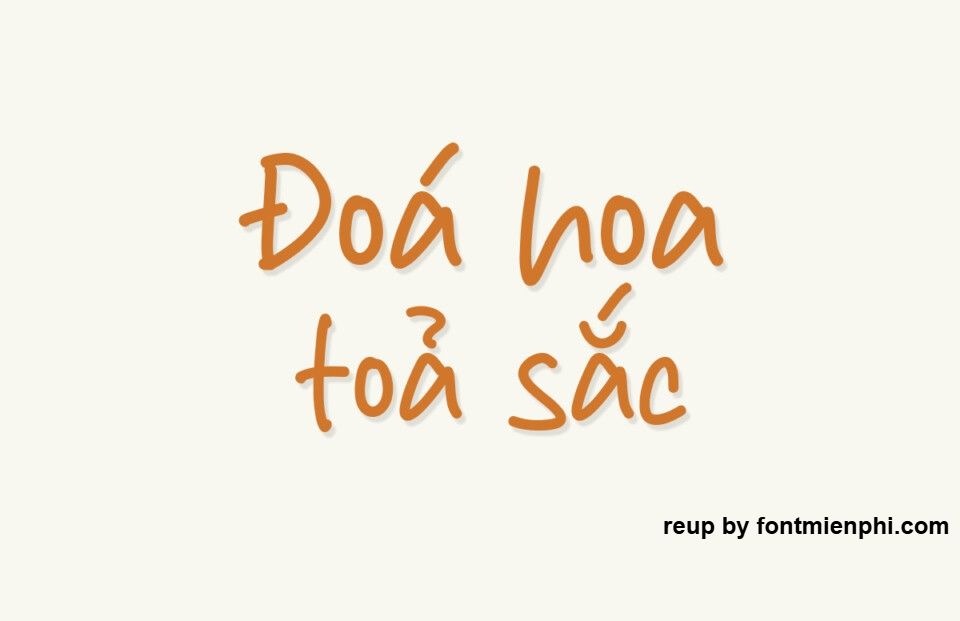
Font Việt hóa 1FTV VIP Privilege People
Font Việt hóa 1FTV VIP Privilege People là giải pháp typography hoàn hảo dành cho các nhà thiết kế đang tìm kiếm sự kết hợp giữa nét hiện đại, tinh tế và sự chuẩn mực trong ngôn ngữ tiếng Việt. Với bộ ký tự được chăm chút kỹ lưỡng cùng các đường nét sang trọng, bộ phông chữ này giúp mọi tác phẩm đồ họa trở nên nổi bật và ghi dấu ấn mạnh mẽ trong lòng người xem. Đây chắc chắn là công cụ không thể thiếu trong thư viện tài nguyên của những ai theo đuổi phong cách thiết kế chuyên nghiệp và đẳng cấp.
Font Việt Hóa 1FTV VIP Privilege People – Phông Chữ Sang Trọng Đột Phá Cho Thiết Kế Đẳng Cấp
Trong thế giới thiết kế đồ họa hiện đại, typography đóng vai trò như cầu nối cảm xúc giữa thương hiệu và khách hàng. Một phông chữ đẹp không chỉ giúp truyền tải thông điệp văn bản một cách rõ ràng mà còn định hình phong cách, gia tăng giá trị thẩm mỹ và khẳng định vị thế của thương hiệu. Nhu cầu sở hữu các bộ font chữ vừa đáp ứng tiêu chuẩn thẩm mỹ quốc tế, vừa hỗ trợ đầy đủ các dấu tiếng Việt một cách mượt mà luôn là bài toán lớn đối với các designer tại Việt Nam.
Font Việt hóa 1FTV VIP Privilege People ra đời nhằm giải quyết triệt để nhu cầu đó. Được phát triển dựa trên cảm hứng từ sự quý phái, độc bản và quyền lực của giới thượng lưu, phông chữ này sở hữu nét chữ sắc sảo, cấu trúc cân đối cùng tỷ lệ hoàn hảo. Quá trình Việt hóa được thực hiện tỉ mỉ, đảm bảo các dấu thanh tiếng Việt (sắc, huyền, hỏi, ngã, nặng) cũng như các chữ cái đặc thù (ê, ô, ơ, ư, đ) được tạo hình tự nhiên, không gây cảm giác gượng ép hay phá vỡ tổng thể cấu trúc ban đầu của phông chữ gốc.
Dù bạn đang thực hiện dự án thiết kế nhận diện thương hiệu cho một khách sạn 5 sao, bộ sưu tập thời trang cao cấp, bìa tạp chí nghệ thuật hay đơn giản là các ấn phẩm truyền thông trên mạng xã hội, 1FTV VIP Privilege People đều có khả năng biến những ý tưởng sơ khai thành những tác phẩm thị giác vô cùng ấn tượng.
1. Bộ Dấu Tiếng Việt Được Viết Hóa Chuẩn Xác Và Tỉ Mỉ
Điểm khác biệt lớn nhất của Font Việt hóa 1FTV VIP Privilege People chính là chất lượng hoàn thiện của bộ ký tự tiếng Việt. Nhiều phông chữ nước ngoài khi chèn dấu tiếng Việt thường gặp phải lỗi lệch khoảng cách, dấu quá to hoặc quá nhỏ làm mất đi sự hài hòa. Với 1FTV VIP Privilege People, toàn bộ hệ thống dấu thanh và chữ cái có dấu đều được thiết kế lại theo chuẩn Unicode, đảm bảo độ cao, góc nghiêng và độ dày nét tương thích tuyệt đối với ký tự gốc. Điều này mang lại trải nghiệm đọc mượt mà, giúp các đoạn tiêu đề dài hay văn bản ngắn đều giữ được sự chỉn chu tối đa.
2. Phong Cách Thiết Kế Sang Trọng, Đẳng Cấp Và Tính Thẩm Mỹ Cao
1FTV VIP Privilege People sở hữu đường nét thiết kế mang hơi hướng hiện đại kết hợp với tinh thần cổ điển vượt thời gian. Sự tương phản tinh tế giữa các nét đậm và nét mảnh tạo nên sự uyển chuyển nhưng vẫn đầy quyền lực. Các đường cong được vuốt nhọn sắc sảo ở các phần chân chữ giúp bộ font có độ bắt mắt cao khi xuất hiện ở kích thước lớn. Phong cách này vô cùng phù hợp với các ngành hàng xa xỉ như bất động sản cao cấp, trang sức, thời trang haute couture, spa & resort, hoặc các thương hiệu muốn định vị bản thân ở phân khúc thượng lưu.
3. Tích Hợp Ký Tự Thay Thế (Alternate Characters) Và Ligatures Phong Phú
Để tăng tính sáng tạo cho người dùng, Font Việt hóa 1FTV VIP Privilege People được tích hợp tính năng OpenType nâng cao với hàng loạt các ký tự thay thế (Alternates) và chữ nối (Ligatures) độc đáo. Tính năng này cho phép các thiết kế gia dễ dàng tùy biến các chữ cái đầu câu, tạo nên những đường uốn lượn nghệ thuật mà không cần phải vẽ tay thủ công. Sự biến hóa linh hoạt của các cặp chữ nối giúp thiết kế logo, typography poster hay tiêu đề bài viết trở nên độc bản, tránh sự trùng lặp và nhàm chán.
4. Khả Năng Ứng Dụng Đa Dạng Trên Nhiều Nền Tảng Thiết Kế
Một phông chữ xuất sắc phải là một phông chữ có độ đa dụng cao. 1FTV VIP Privilege People đáp ứng hoàn hảo yêu cầu hiển thị trên cả hai môi trường: in ấn (Print) và kỹ thuật số (Digital). Bạn có thể sử dụng font này cho các ấn phẩm in ấn chất lượng cao như bao bì sản phẩm, thiệp mời sự kiện VIP, brochure, catalogue, bìa sách; hoặc áp dụng vào thiết kế banner quảng cáo, giao diện website, ứng dụng di động và hình ảnh mạng xã hội. Ở bất kỳ quy mô hay độ phân giải nào, phông chữ vẫn giữ được độ sắc nét và tính rõ ràng tuyệt đối.
5. Tối Ưu Hóa Tỷ Lệ Kerning Và Spacing Chuyên Nghiệp
Khoảng cách giữa các chữ cái (Kerning) và khoảng cách giữa các dòng (Spacing) trong 1FTV VIP Privilege People đã được hiệu chỉnh tự động một cách chuẩn xác. Người dùng không cần mất quá nhiều thời gian để canh chỉnh thủ công từng cặp chữ cái khi gõ văn bản. Tỷ lệ phân bổ không gian hợp lý giúp câu chữ trông thoáng đãng, cân đối, tăng khả năng đọc hiểu nhanh chóng mà vẫn duy trì được sự tinh tế vốn có của một dòng font cao cấp.
Ứng Dụng Thực Tế Của Font 1FTV VIP Privilege People Trong Các Dự Án Creative
Sự linh hoạt của phông chữ này giúp nó trở thành sự lựa chọn hàng đầu cho nhiều loại hình thiết kế khác nhau. Dưới đây là những ứng dụng phổ biến nhất mà bạn có thể trải nghiệm: